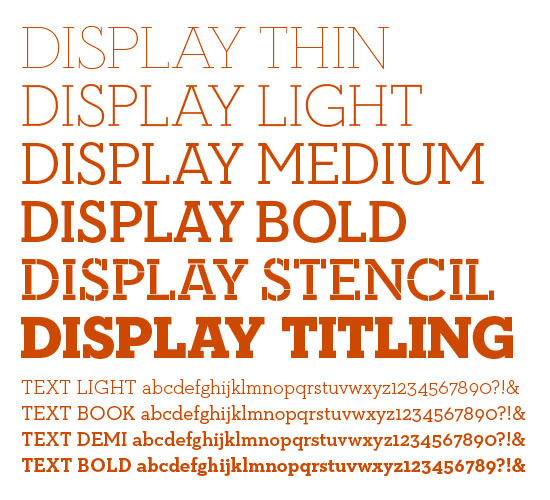
Neutraface Slab (House Industries)
From fine print and red ink in corporate annual reports to huge three dimensional signage, Neutraface has become the definitive designers' workhorse. Now this geometric juggernaut boasts even more font firepower with the addition of the Neutraface Slab family. Neutraface Slab features five display weights, four text weights with italics plus a unique stencil style that work together like a typographic symphony or can stand alone like accomplished soloists. Just like its sans-serif counterparts, Neutra Slab Text includes integrated small caps, seven figure styles and a host of other sophisticated OpenType features that have bee integrated in a single seamless package. The complementary display weights afford an uncompromising statement that can range from thin and delicate to bold and bombastic.
Ja- thin und stencil sehen zwar sehr gut aus aber den Rest habe ich mindestens schon fünfmal zum verwechslen ähnlich im Fontexplorer.
aber trotzdem schön sowas zu haben, ist zwar eine fast komplett andere schrift geworden aber trotzdem schön sowas pasend zu neutraface zu finden. sie thin sieht interessant aus, die serifen am S wirken da irgendwie nicht so ... aber trotzdem die slab hat was.
Was sollen denn diese völlig unsinnigen Einschnitte bei der Stencil?